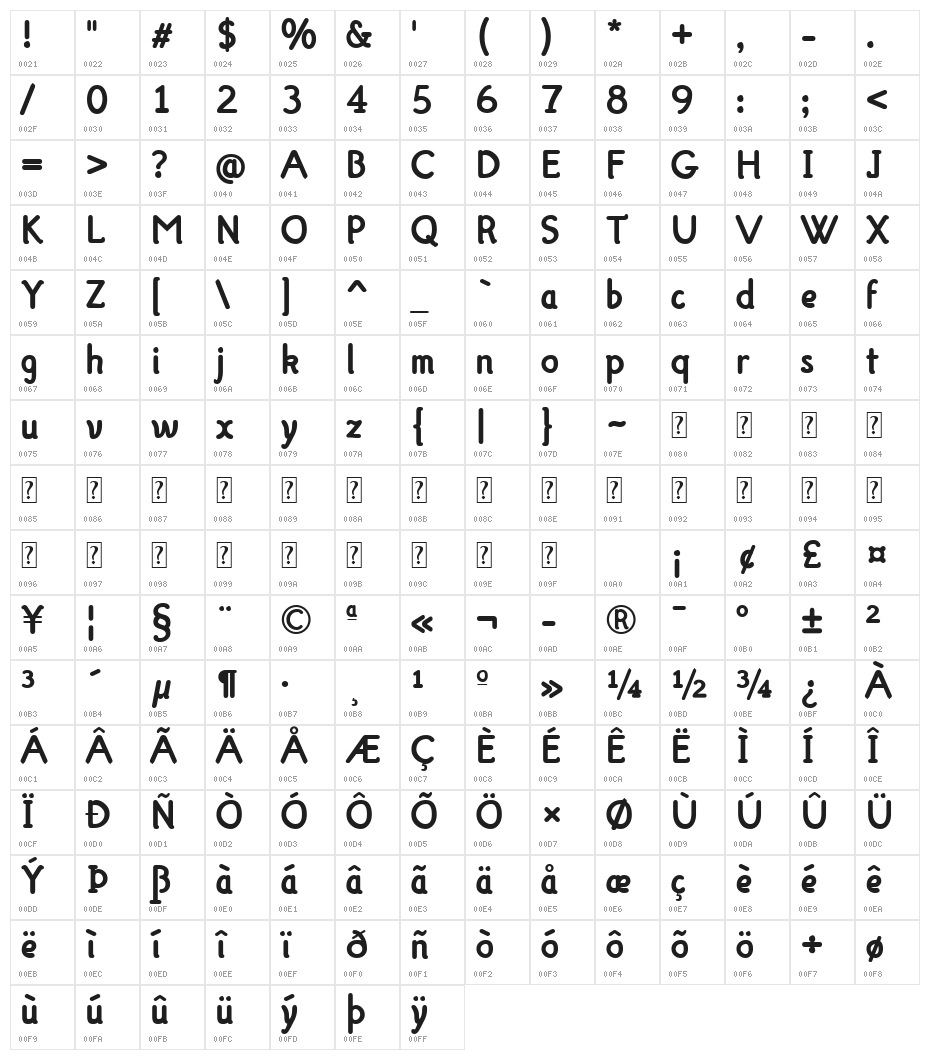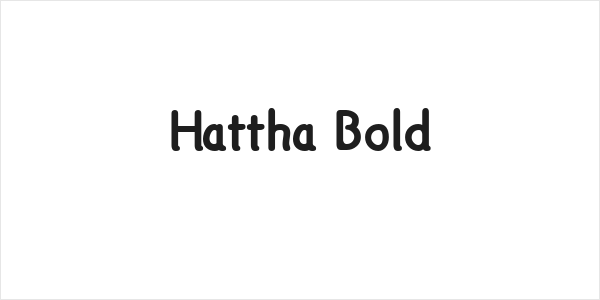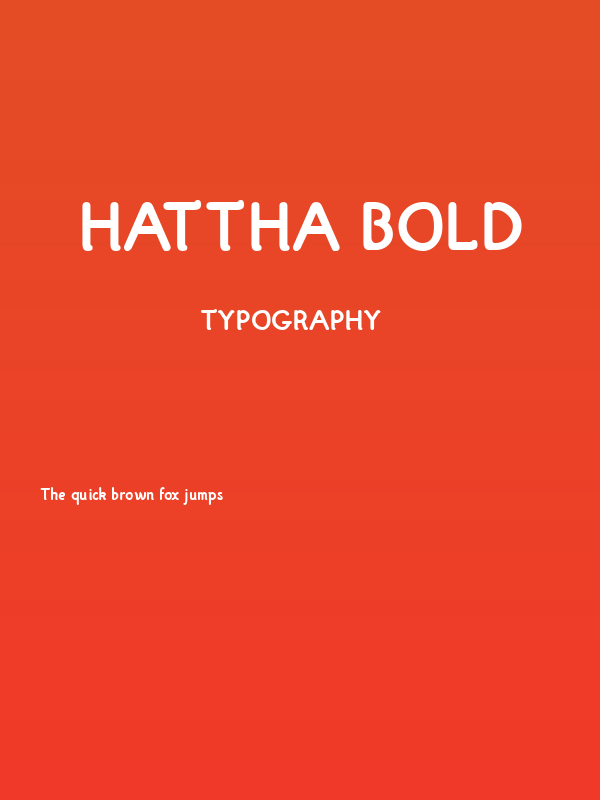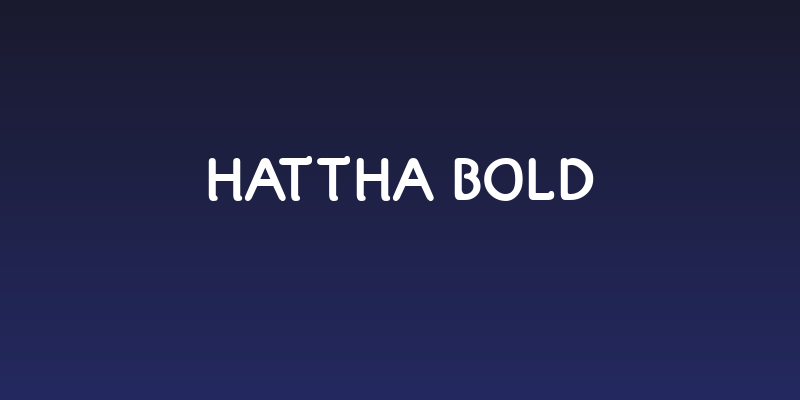
Hattha Bold Font
| Gesamtstil | Playful |
| Anwendungsfall | Headlines, Logos, Informal Text |
| Vorgeschlagene Projekte | Ideal for children's books, casual branding, playful advertising, and informal invitations. |